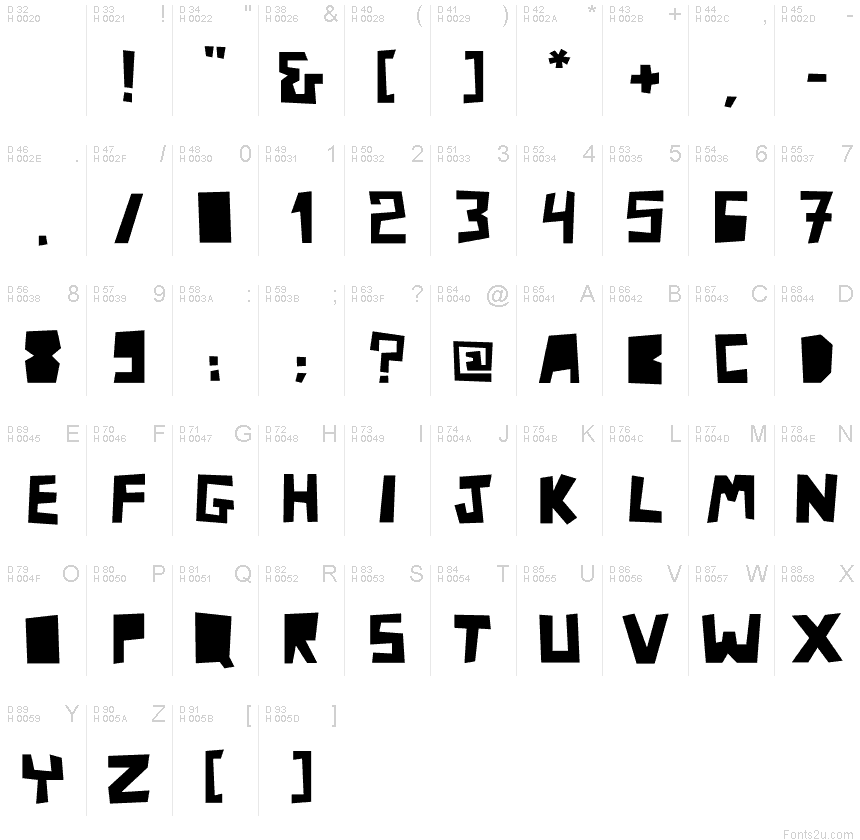
خط Caliqueña من Lacamorra هو خط عرض مجاني بنمط قصص مصورة من عائلة Caliqueña. تبدو أشكاله الضخمة المقطوعة يدوياً وكأنها أحرف من ورق أسود عُلقت على عجل؛ فهي طويلة، مائلة قليلاً، ومتقاربة جداً، مما يمنح حتى الكلمات القصيرة طابعاً مرحاً وقوة تأثير تشبه ملصقات الشوارع.
يعمل Caliqueña بشكل رائع مع ملصقات المهرجانات، وتغليف الوجبات الخفيفة، ومنشورات فعاليات الأطفال، وتصاميم الملصقات (ستيكرز)، والمجلات المستقلة، وصور مصغرة لليوتيوب، والرسومات الجريئة على وسائل التواصل الاجتماعي. استخدم Caliqueña بحجم كبير إلى حد ما ليبقى إيقاعه المتعرج واضحاً، وقم بإقران هذا الخط المجاني بخط sans serif بسيط عندما تحتاج إلى نص مساند أكثر هدوءاً.